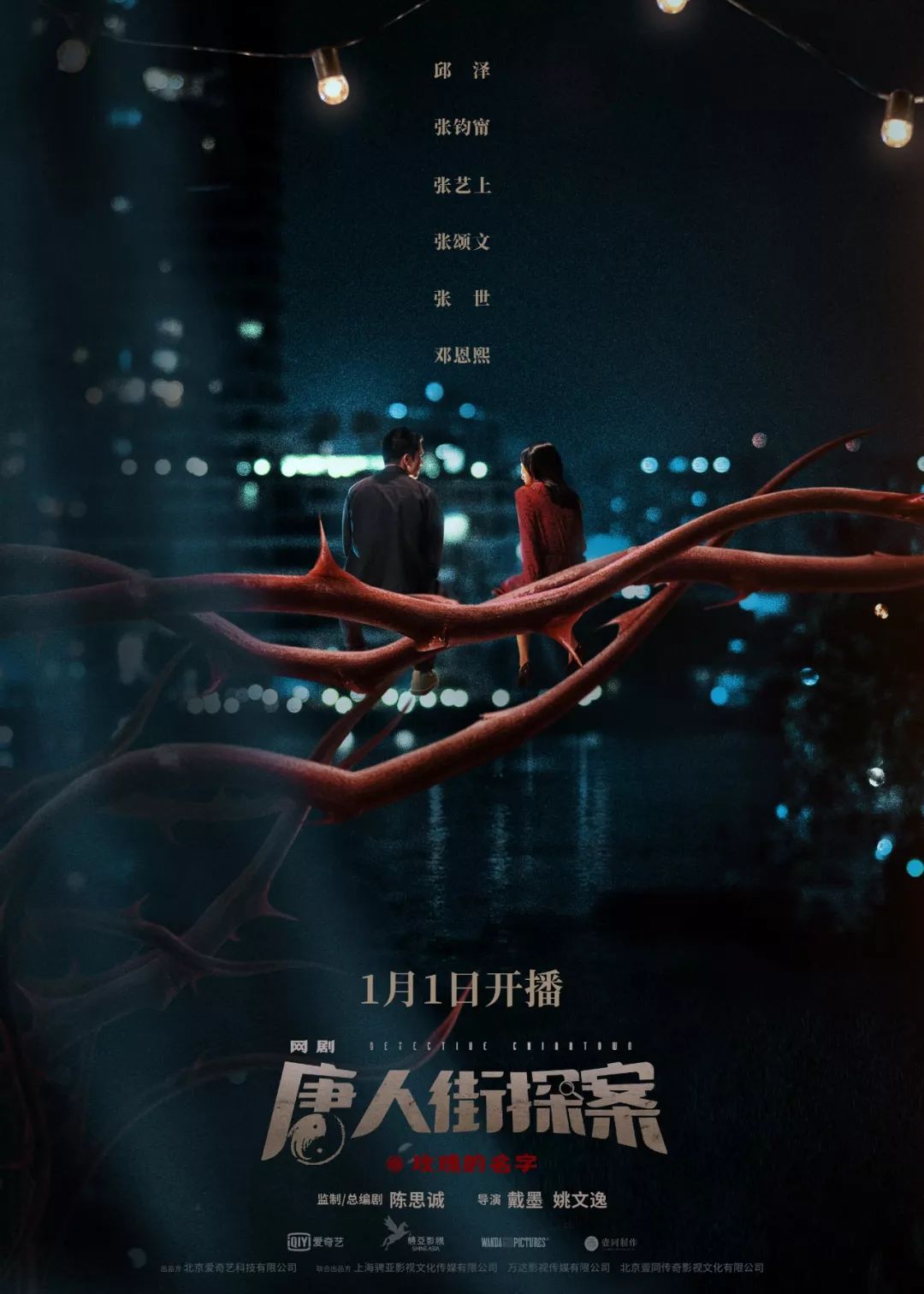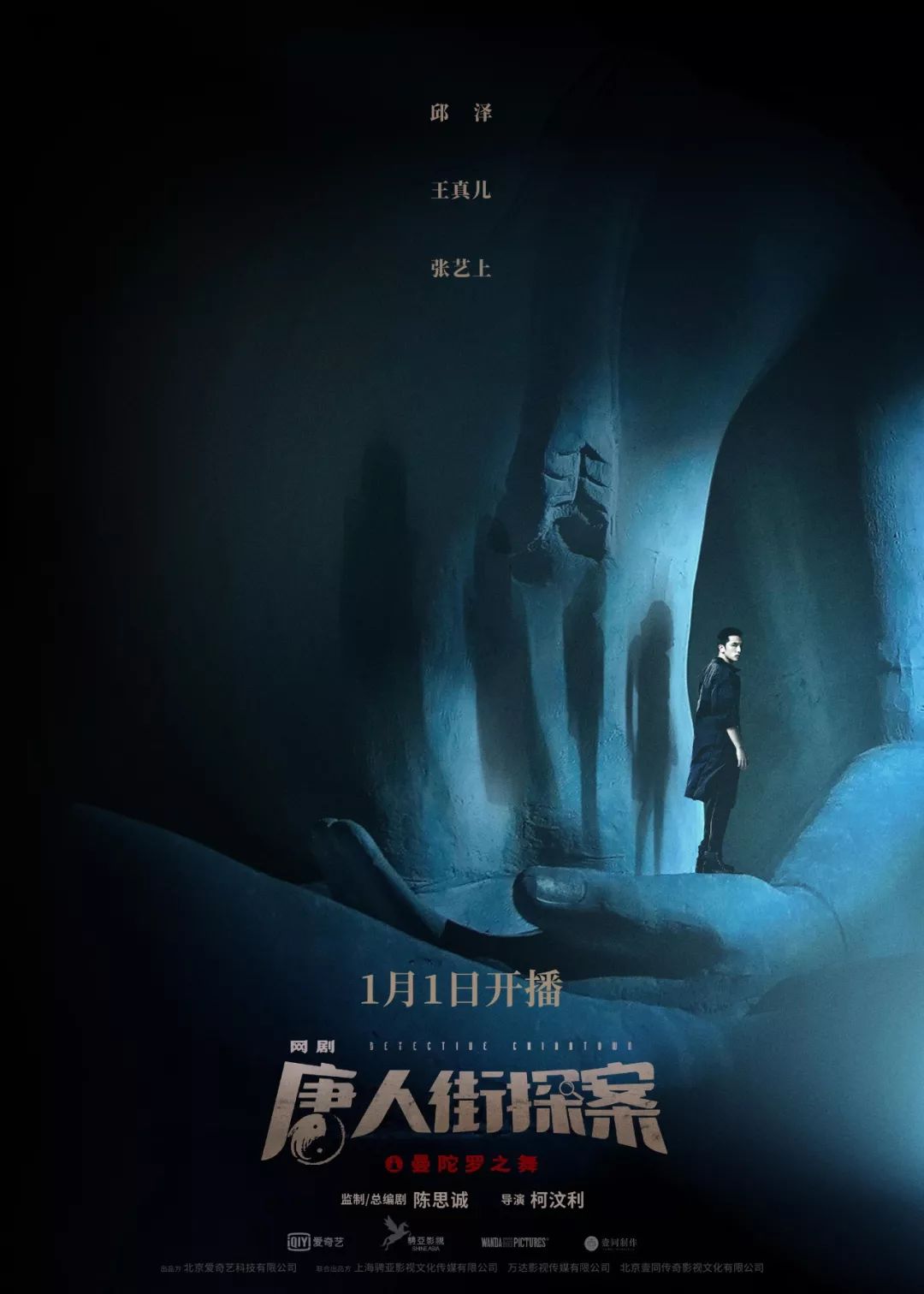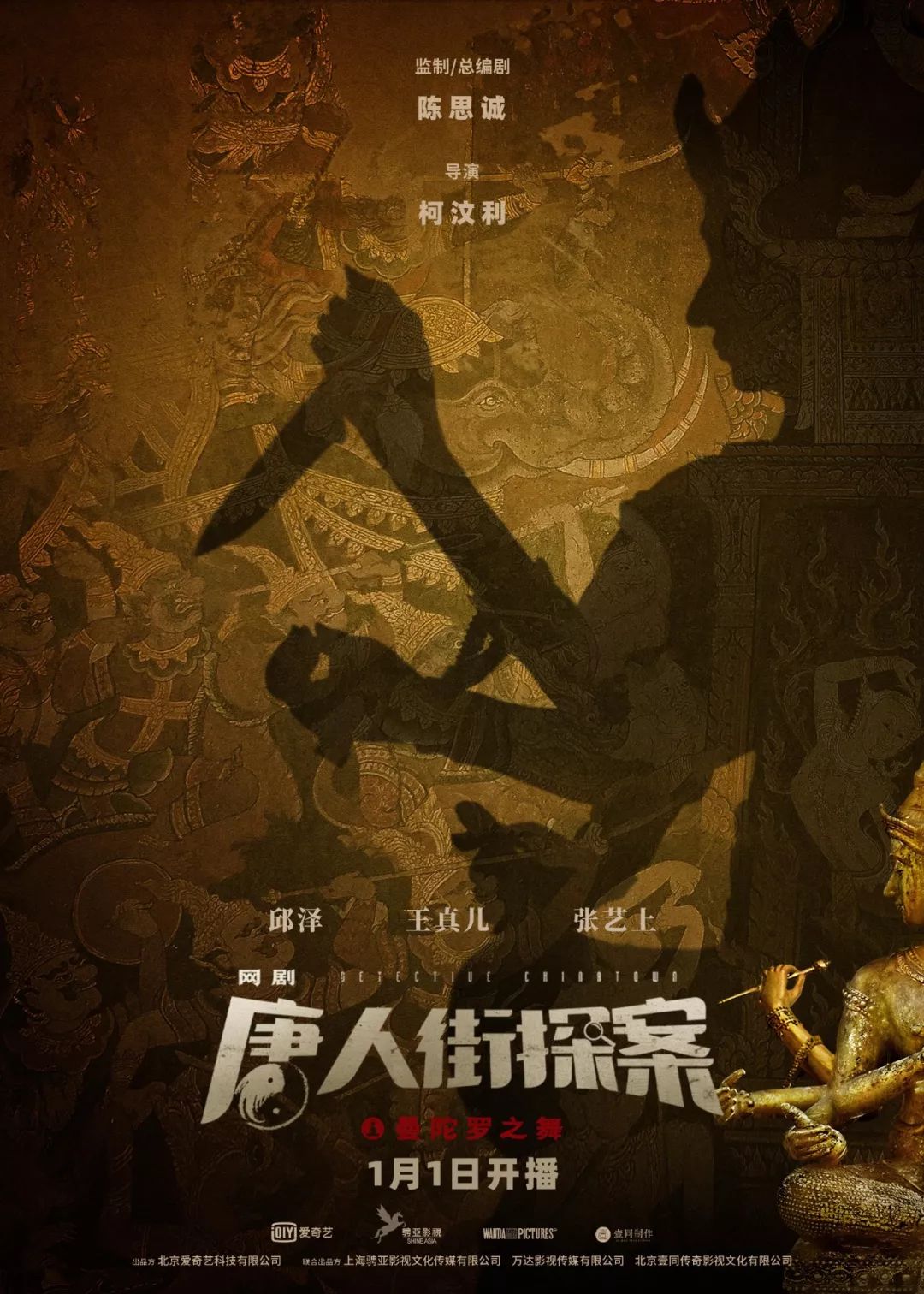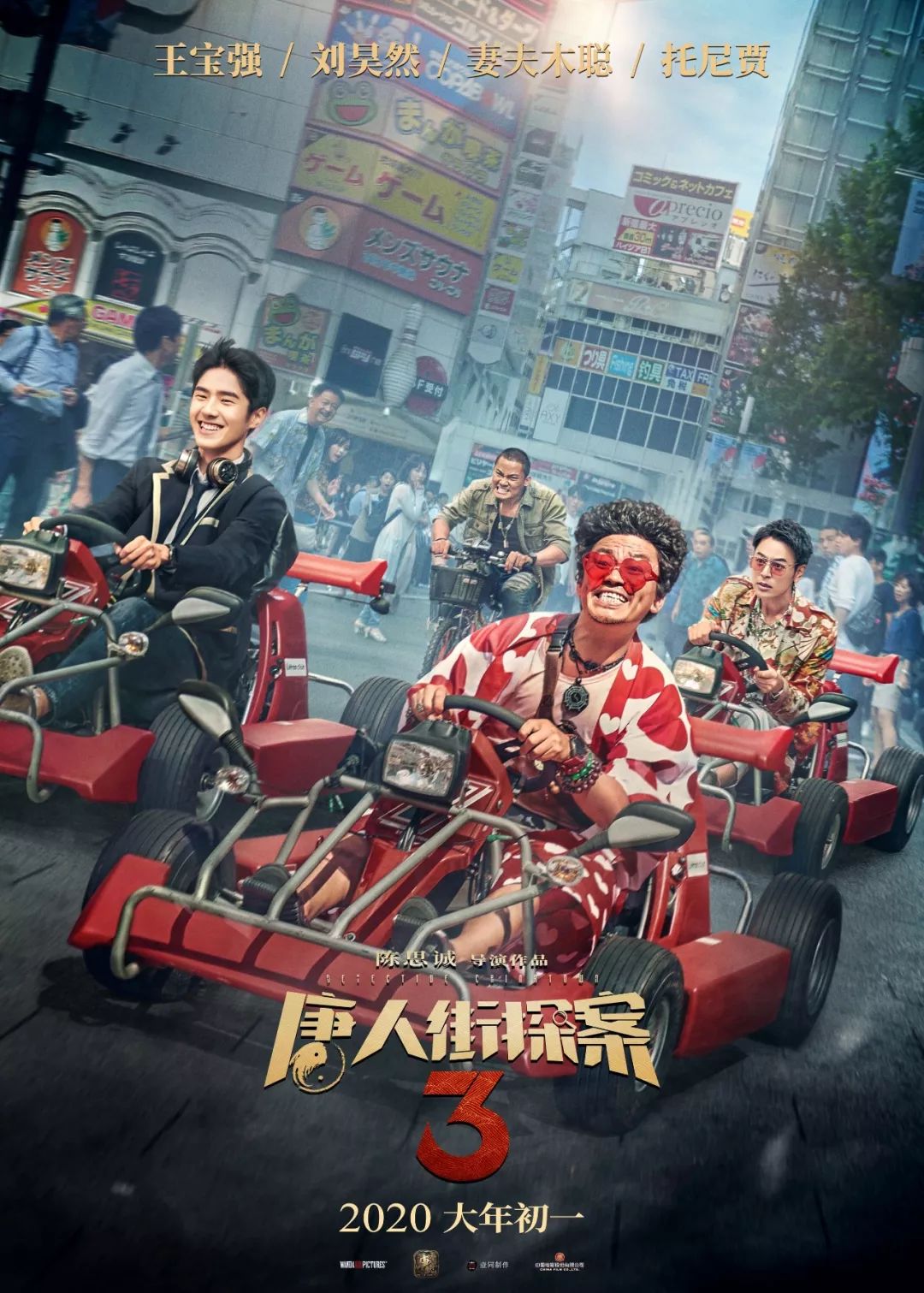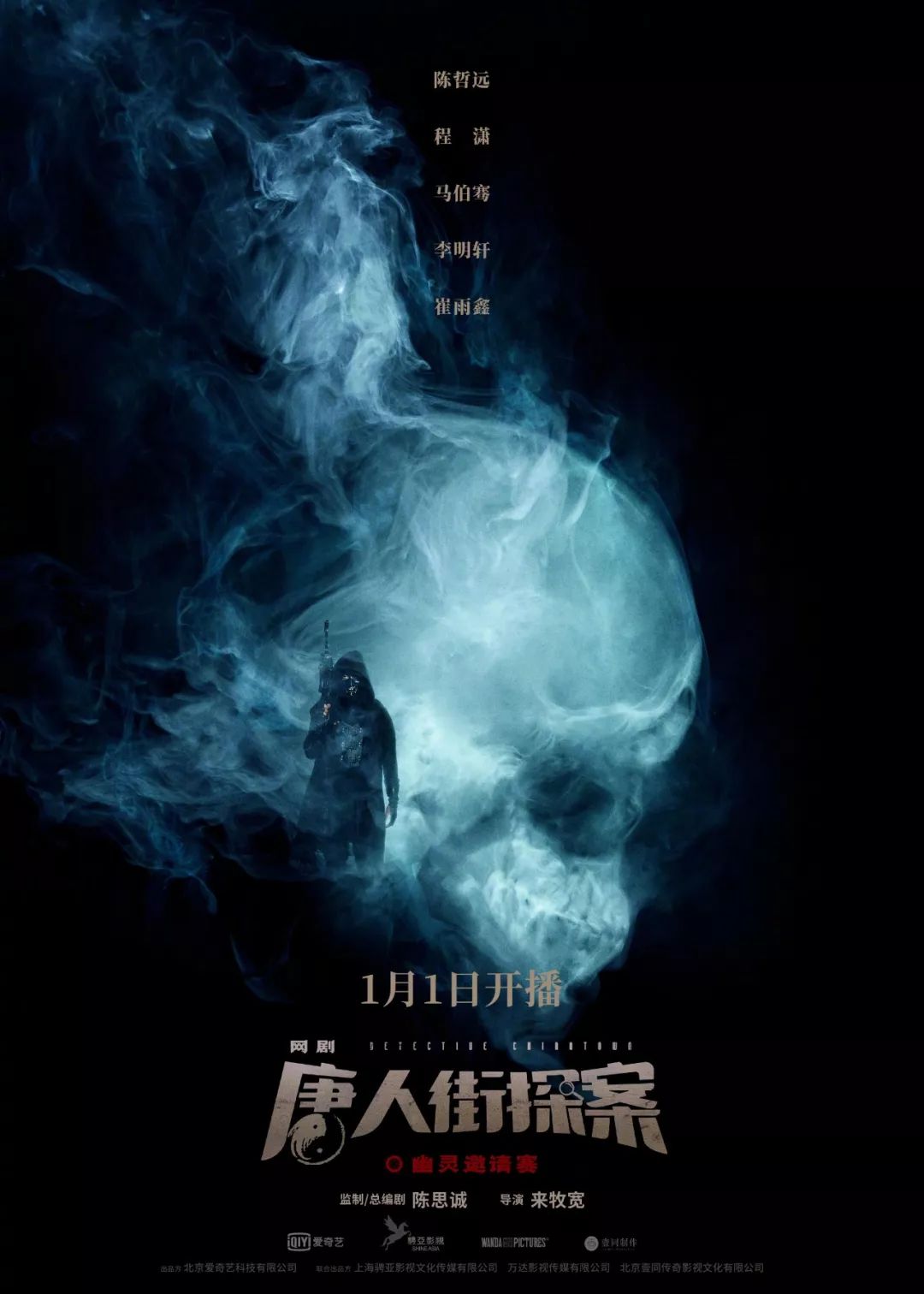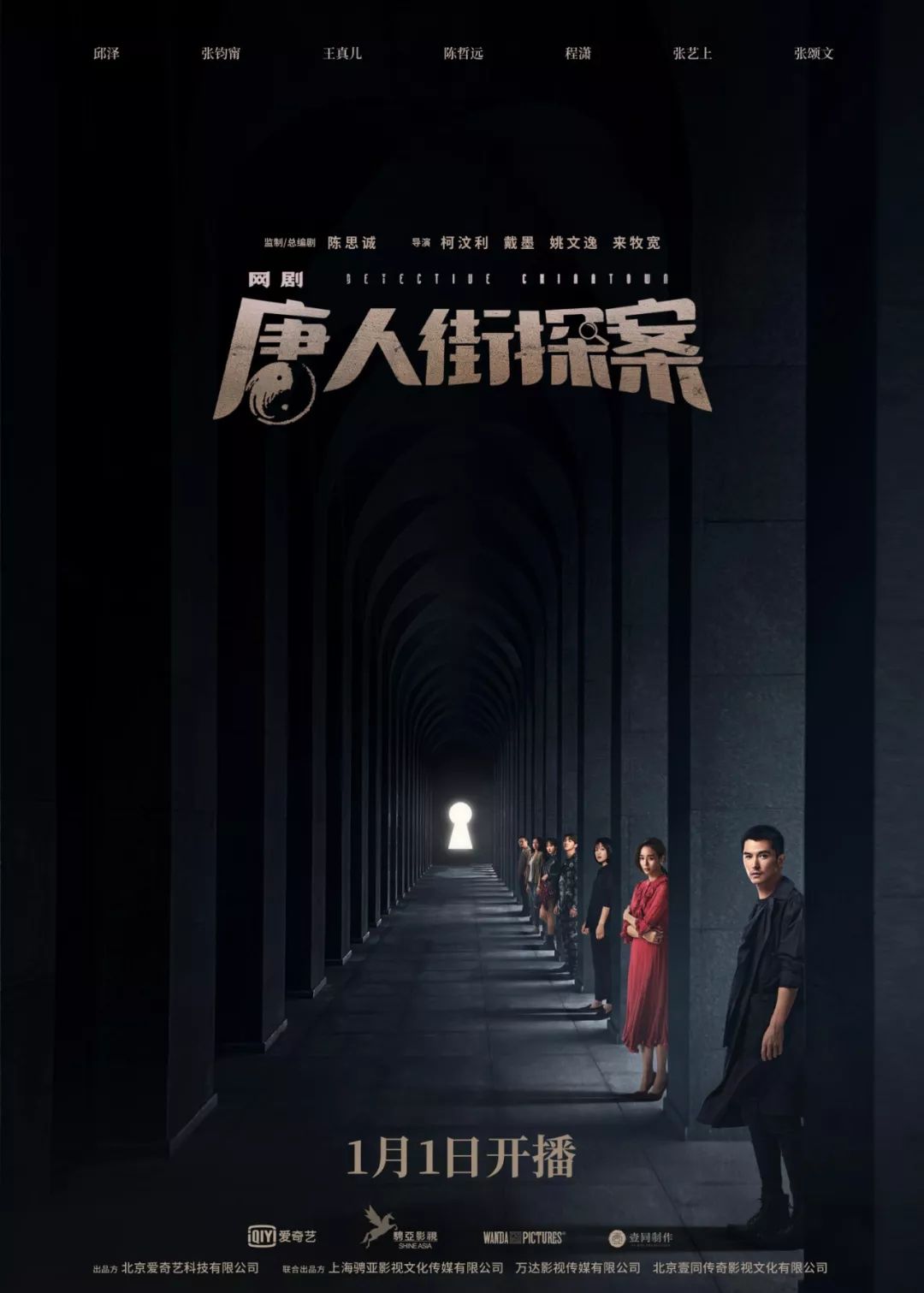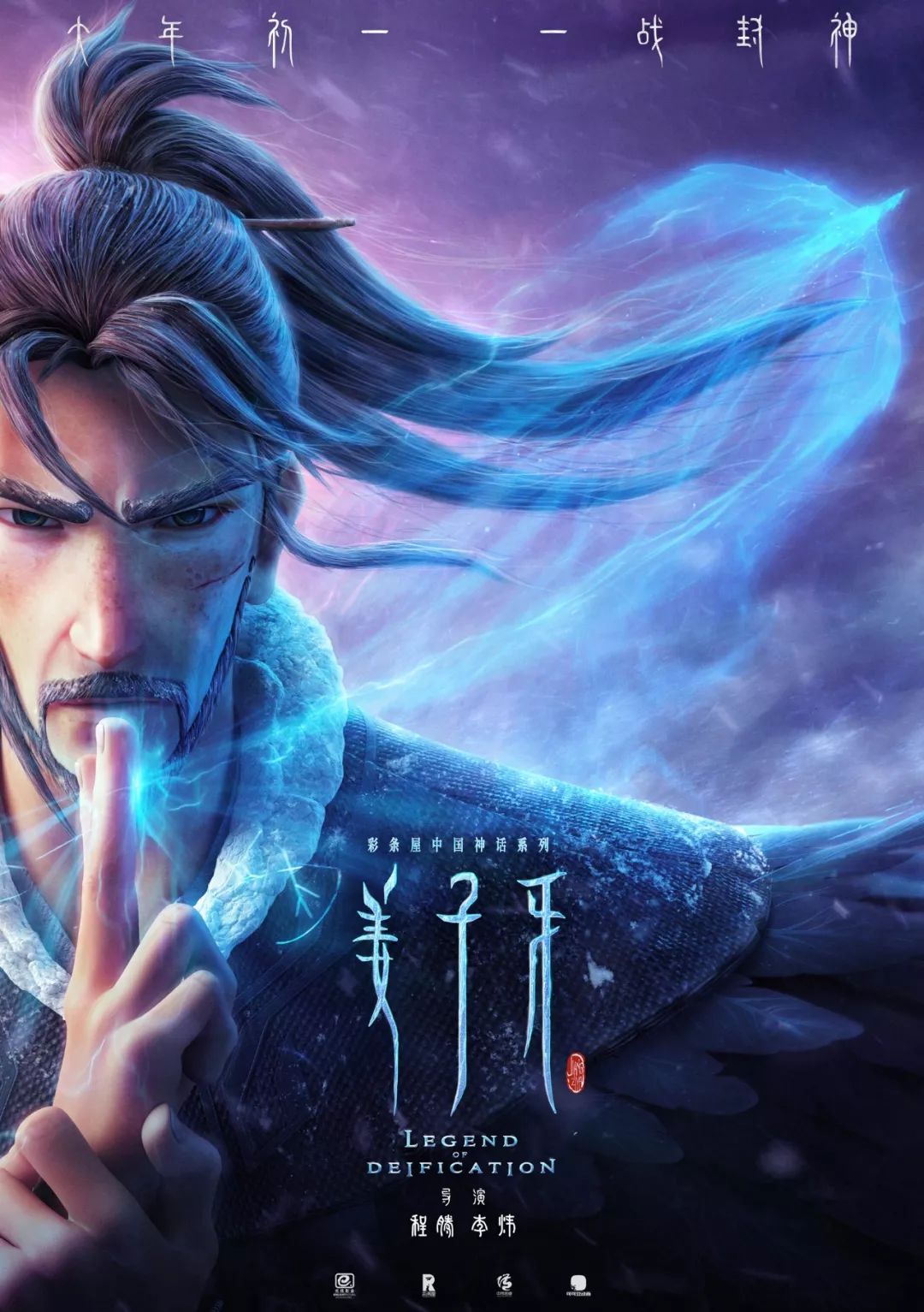
大年初一电影海报汇集,你pick哪个?
所以今天柚子就来盘点一下大年初一的贺岁档,pick一下好看的电影……海报。
唐人街探案3
要说大年初一最火,也是柚子最期待的非《唐探3》莫属,陈思诚下了好大一盘棋,打造了唐探宇宙。
从最近热门的《唐人街探案》网剧就能看出来,豆瓣评分8.0,每集都是按照电影的品质在打造,比如第一个故事——《曼陀罗之舞》,林黑犬背后站着四个女人的影子,四周是巨大的佛像……
这张更神秘,用实物和影子的对比,加重了鬼神说的色彩。
刚播完的《玫瑰的名字》,当看到这一幕时,还以为是男女主角真的爱了,但带刺的玫瑰荆条,马上告诉你,这都是假的……
下周还剩最后一个故事——《幽灵邀请赛》,巨大的骷髅头跟烟雾相结合,散发着恐怖的气息,只可惜看不到林黑犬了……
不过吸吸迷宫海报也是好的~
而且电影《唐探3》会在网剧播出一周后无缝连接,到时还会看到林黑犬和IVY(话说这张纵深缩小构图可还行)。
希望一定要比网剧精彩啊,毕竟已经把胃口吊得这么高了,哈哈哈!
下面这个预告片,相信你已经看过~
毕竟到了酷你吉娃tokyo的地盘,所以字体用了白舟忍者~
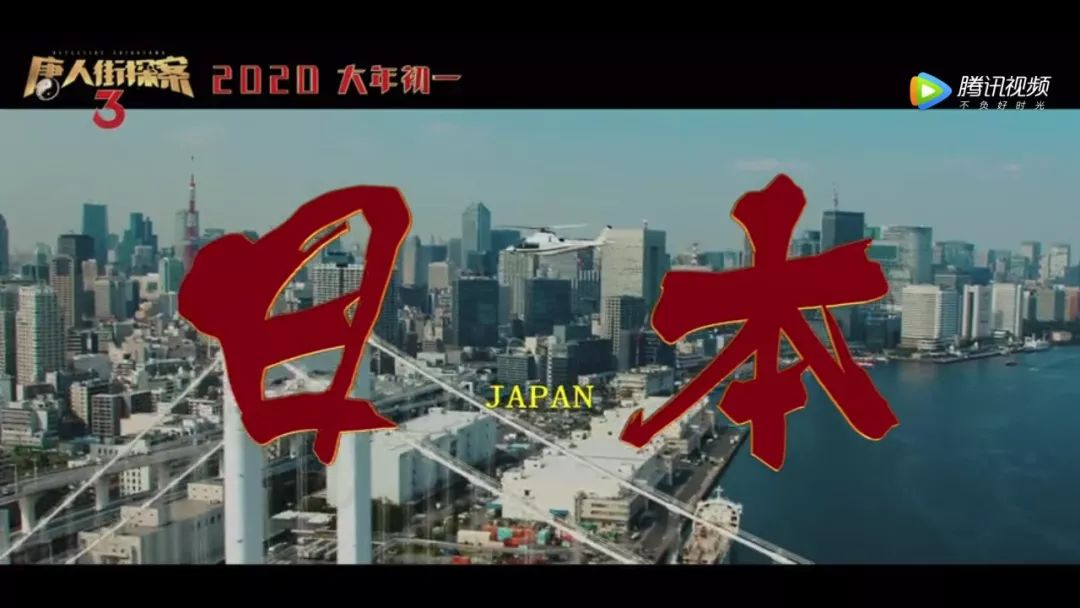
它很有日本的风格,看起来也比较凌厉,唯一的缺点是中文字不全。
所以字由上也有另一款相似“文悦青龙体”,笔画偏细些。
除了白舟忍者,我还发现它的宣传图上,用了庞门正道粗书体,看起来颇有喜感(看来唐探3要把毛笔字用到底)。
姜子牙
国漫之光的《姜子牙》也是我很想看的,尤其是看到预告,就心痒痒~
再品品它的海报,彻底沦陷……
为了配合人物的细长画风,“姜子牙”三个字,也选择了以金文为主的字形,很有中国传统文化的意味~
这类字体字由上也有,比如华康金文体。
我还捕捉到一张哪吒和姜叔的同款海报,用的汉仪迪升英雄体。
这次的古老神话,能带给我们什么惊喜?
中国女排
作为主旋律电影第三部,中国女排也是备受期待,特别是陈可辛、巩俐这两块金字招牌,还有那么多中国女排成员的真实演绎,肯定会让人振奋不已!
海报也是跟电影基调一样,透着浓浓的怀旧复古风~
字形是在宋体的基础上,做了断笔画处理,加入了凌厉的笔锋,看起来跟中国女排一样坚强,永不服输!
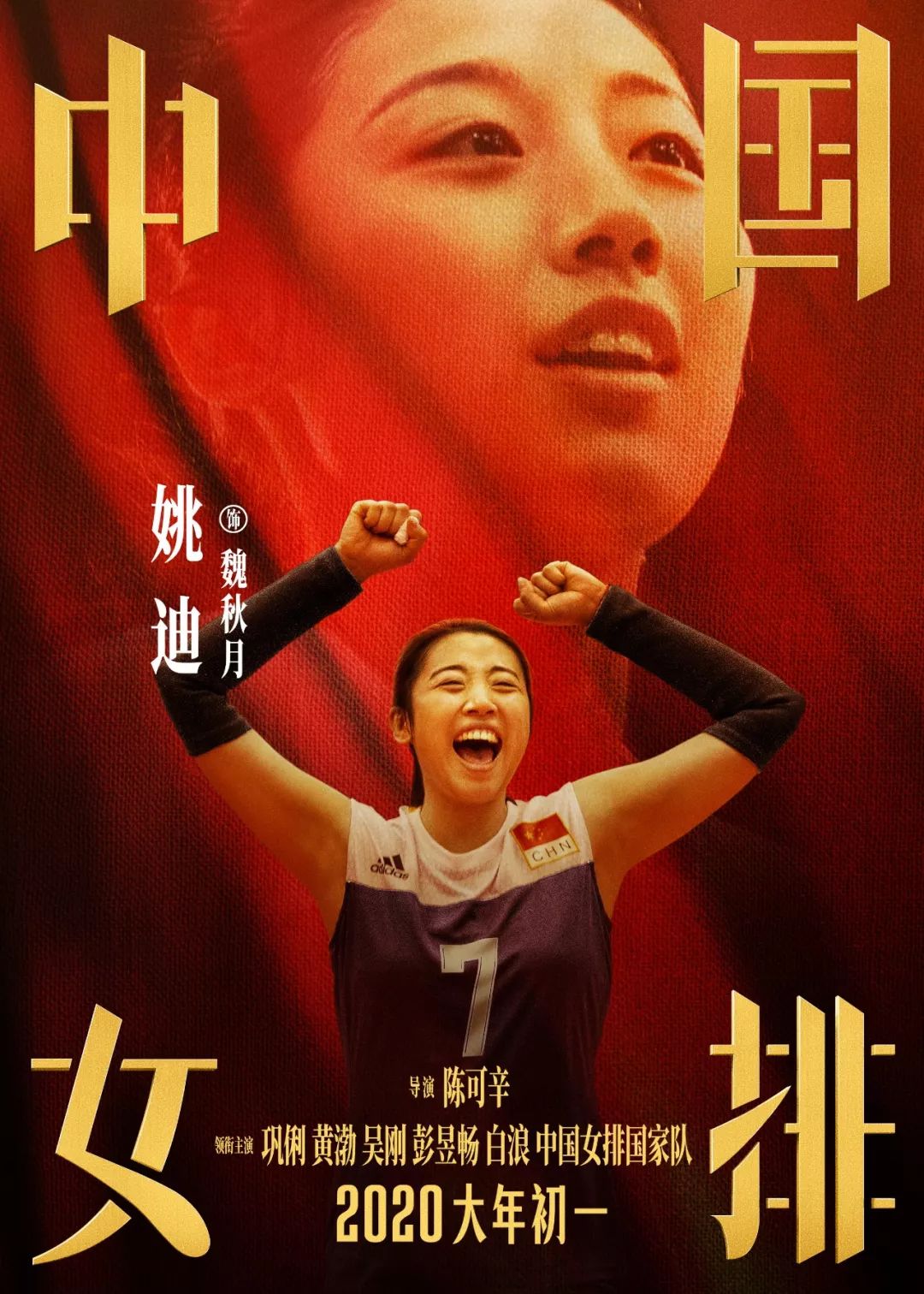
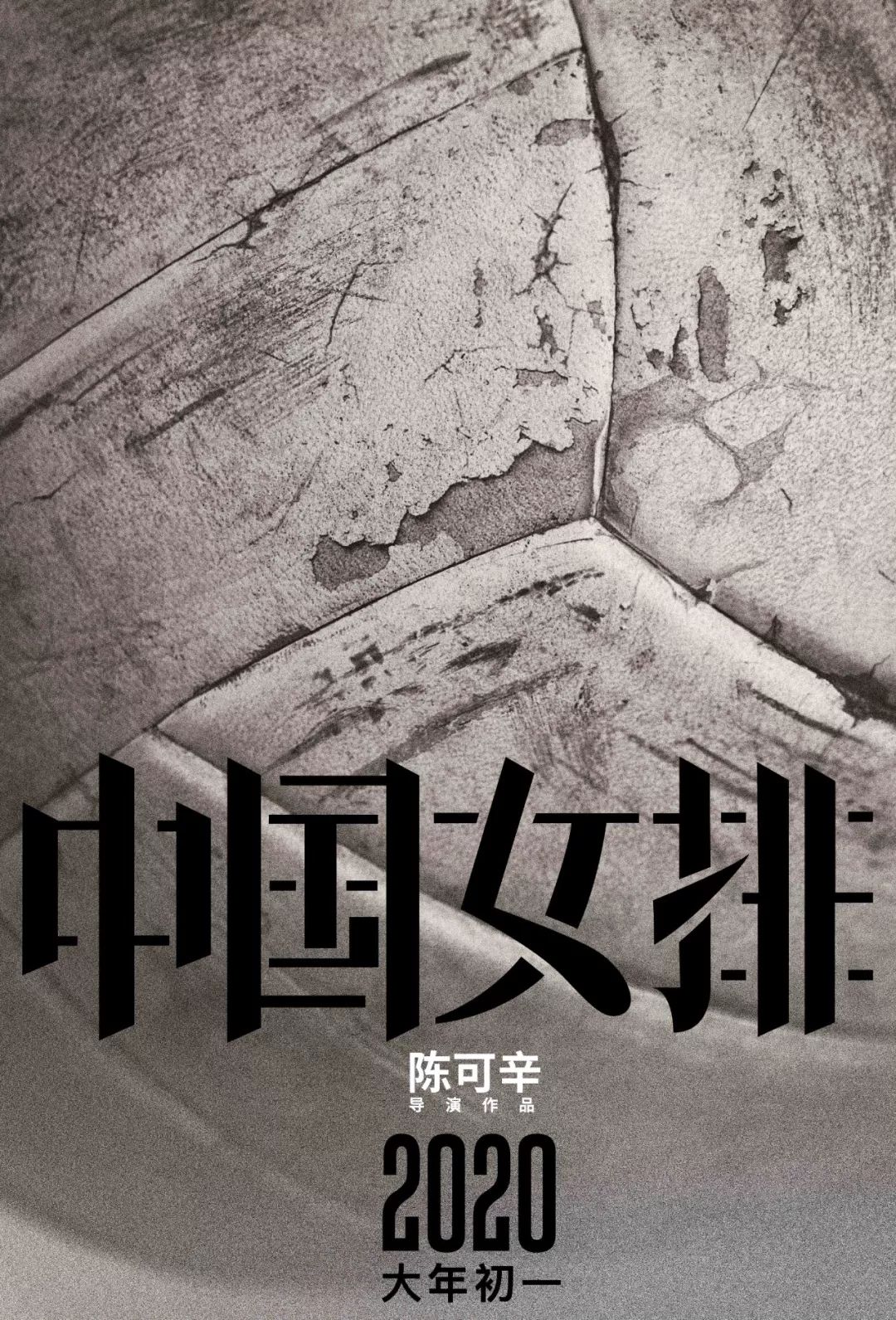
大年初一还有《囧妈》、《紧急救援》值得看,它们一个逗趣,从电影名字设计就能看出~
一个火力全开,以大字作为背景,层叠交错,满屏都是溢出的男性荷尔蒙~